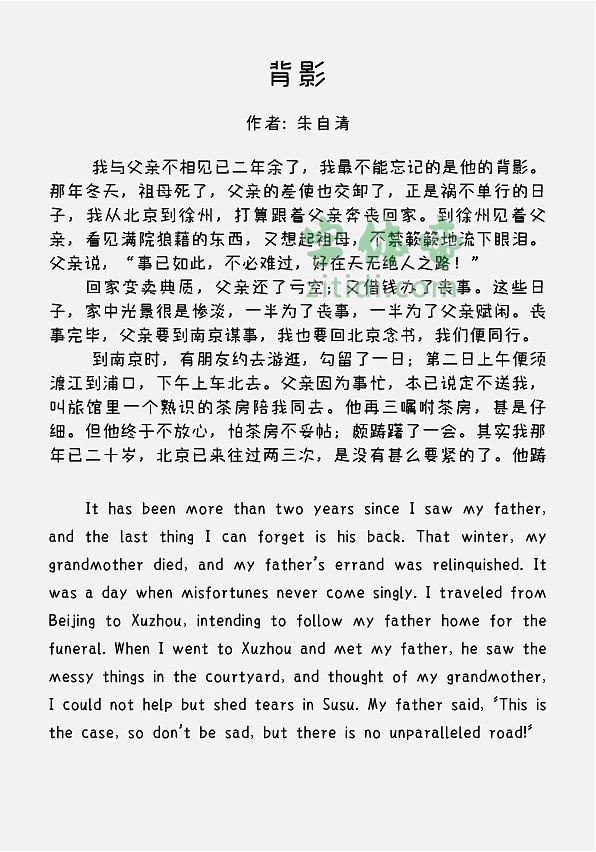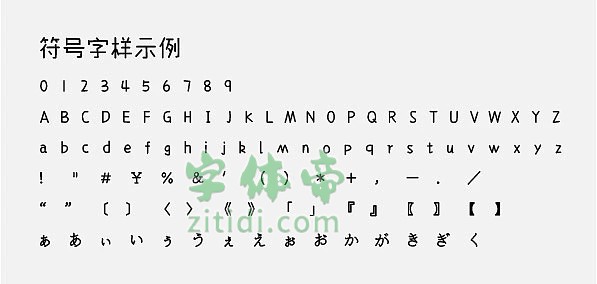
字帮玩酷体字体信息
2022年,我们将精力始终如一的放在这款字体上,无论是质量还是数量,我们团队都非常有信心它可以带给大家更有趣、更丰富的使用感受。
我们将这套字体取名“字帮玩酷体”,像名字一样,它的字形风趣,笔画多元,字形错落有致,风格轻松玩趣,收录GBK编码共20923个文字及987个符号,满足各种使用场景。相信大家在打一些生僻字时会有“被默认”的情况,字体很难统一,但字帮玩酷体无论是常用字还是生僻字都不会让大家有这样的烦恼。
“字帮玩酷体”是一款书写很新颖的字体,字体大方,适合各种设计作品使用!欢迎下载!